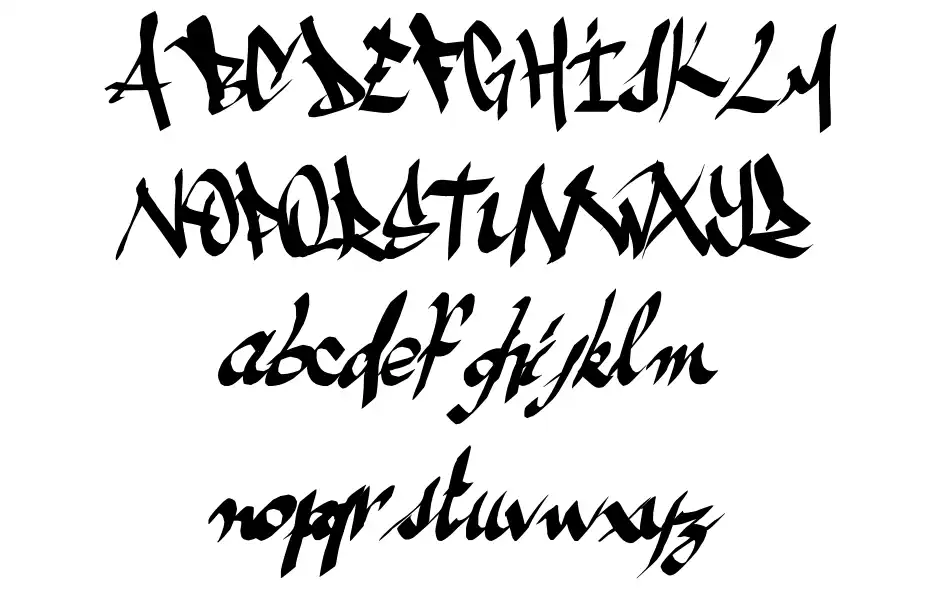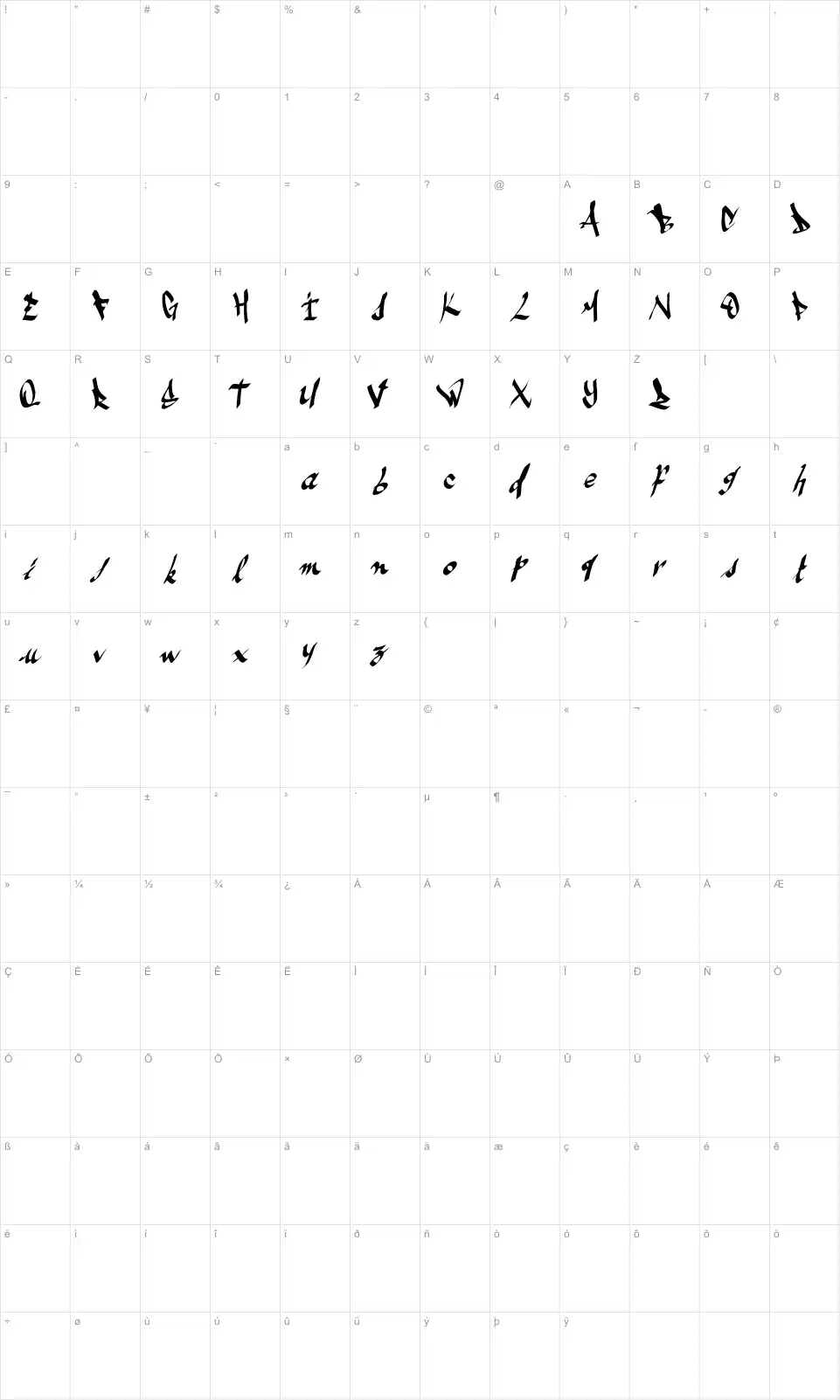
Ameze’s Font é uma fonte Script ideal para quem procura uma grafia dinâmica e moderna. Ela foi criada pelo designer Ameze e é perfeita para aplicativos como design gráfico, publicidade e criação de logotipos. Esta fonte, em formato TTF, está disponível gratuitamente para uso pessoal e possui uma categoria de Graffiti, que a torna única e distintiva. Com 14 KB de tamanho, ela é compacta e rápida para carregar. Adicionada em 12 de julho de 2022, já contabiliza mais de 14.500 downloads. Para quem está procurando uma maneira de experimentar Ameze’s Font antes de usar, é possível gerar uma pré-visualização personalizada online para ver como a fonte se sentirá em textos e gráficos. Visite o site do designer: http://perso.wanadoo.fr/amezeworld para mais informações sobre Ameze’s Font.
Designer: Ameze